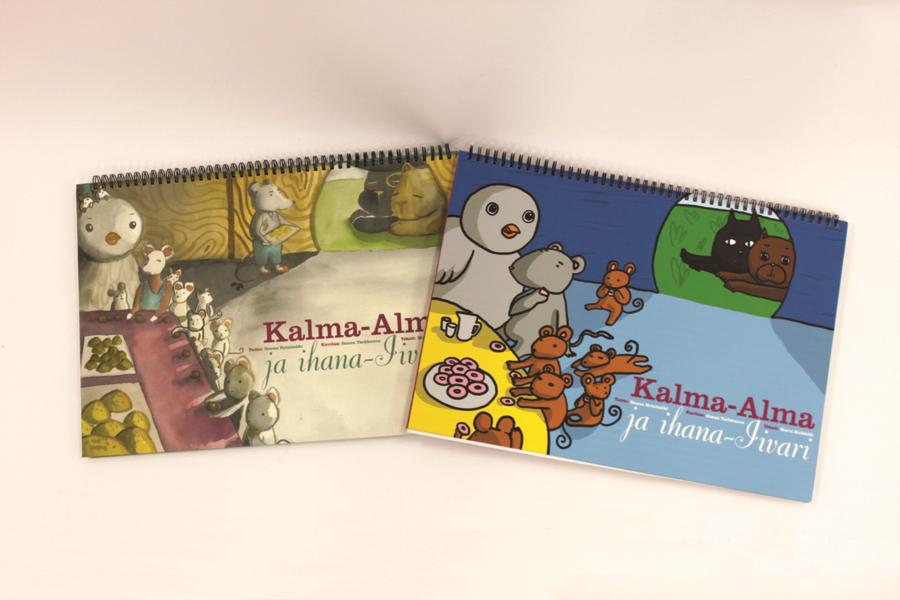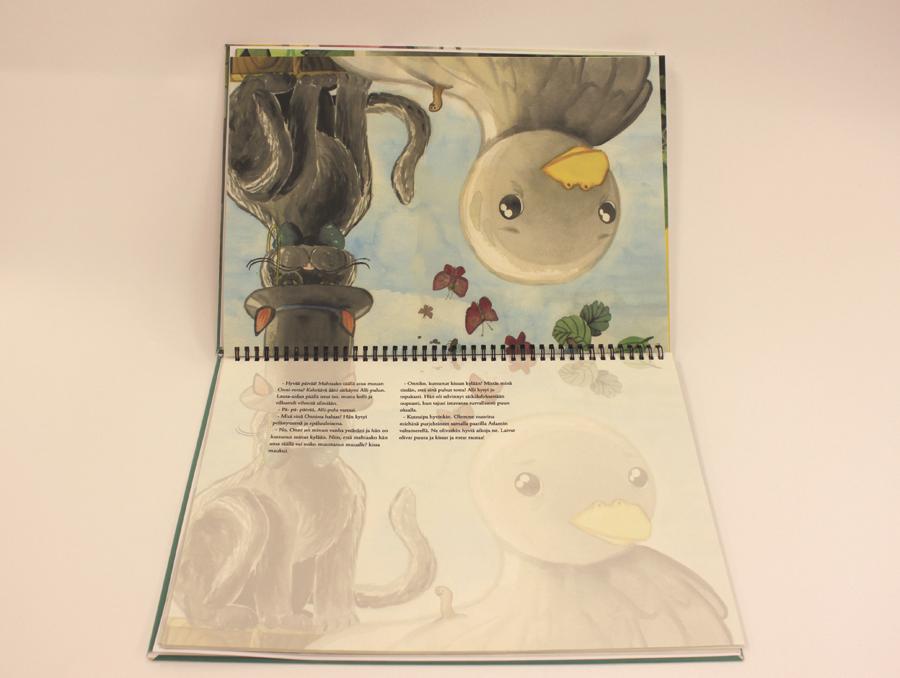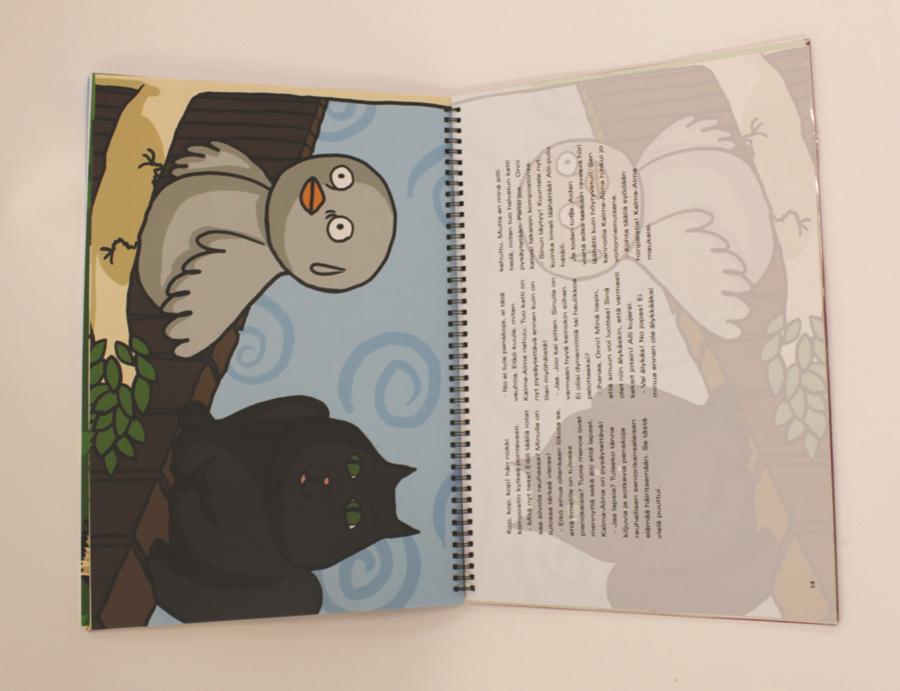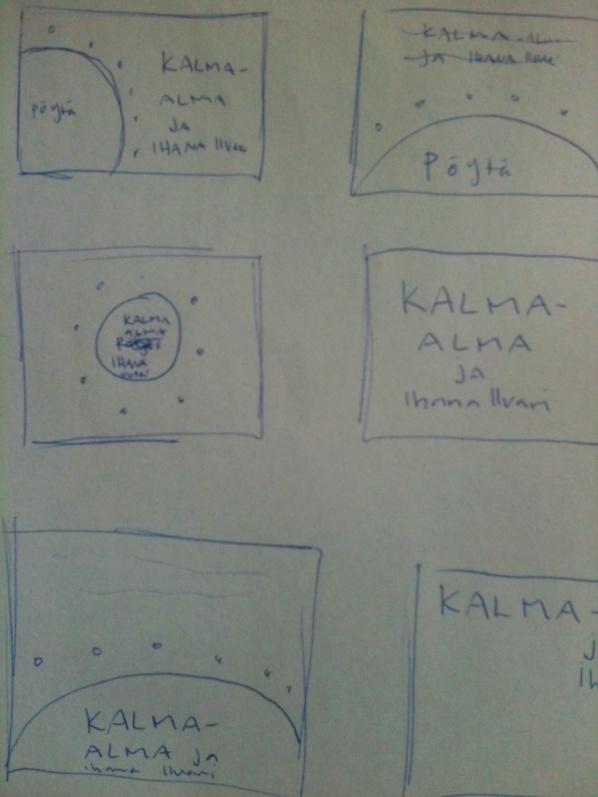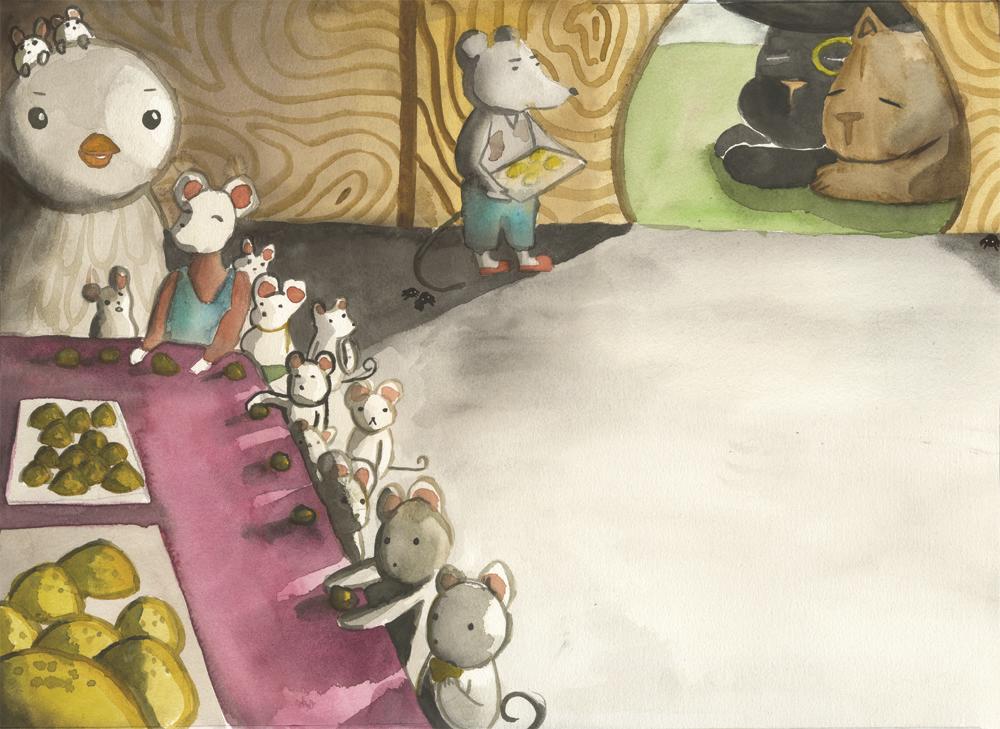
Henna Heinimäki. Taitto ja typografia lasten kuvakirjalle kirjastokäyttöön. Opinnäytetyö Kevät 2012 Kulttuurin yksikkö Muotoilun koulutusohjelma
1 Henna Heinimäki Taitto ja typografia lasten kuvakirjalle kirjastokäyttöön Opinnäytetyö Kevät 2012 Kulttuurin yksikkö Muotoilun koulutusohjelma
2 1(49) SEINÄJOEN AMMATTIKORKEAKOULU Opinnäytetyön tiivistelmä Koulutusyksikkö: Kulttuurin yksikkö Koulutusohjelma: Muotoilun koulutusohjelma Suuntautumisvaihtoehto: Graafinen muotoilu Tekijä: Henna Heinimäki Työn nimi: Taitto ja typografia lasten kuvakirjalle kirjastokäyttöön Ohjaaja: Saija Sillanpää ja Anne Kuusela Vuosi: 2012 Sivumäärä: 49 Liitteiden lukumäärä: 7 Opinnäytetyön aiheena oli suunnitella taitto ja typografia lasten kuvakirjalle. Kirja on suunnattu kirjaston satutunneille. Kirjasta oli kaksi protoa, joita testattiin. Protokirjassa oli erilaisia taitto ja typografia valintoja, joista lukija valitsi toimivimman ratkaisun. Tutkimusmenetelmänä oli haastattelu, jonka avulla kerättiin kokemusperäistä tietoa lopullisen kirjan tekemiseen. Haastattelut tapahtuivat satutunnin jälkeen haastattelemalla lukijaa. Teoriaosuudessa tarkastellaan myös mediakasvatusta satutunneilla. Avainsanat: Taitto, typografia, lastenkirja
3 2(49) SEINÄJOKI UNIVERSITY OF APPLIED SCIENCES Thesis abstract Faculty: School of culture and design Degree programme: Culture and Design Specialisation: Graphic Design Author/s: Henna Heinimäki Title of thesis: Folding and typography for children s picture book. Supervisor(s): Saija Sillanpää ja Anne Kuusela Year: 2012 Number of pages: 49 Number of appendices: 7 The goal of my thesis was to design folding and typography for children's picture book. The book was designed to be used in children's story hours in libraries. There were two prototypes of the book, which I tested. In the book there were various different folding and typography options of which the reader chose the best alternative. As a research method I used interviews which helped me to gather empirical data for making the final version of the book. The interviews took place after the story hour. In addition, in the theoretical part I reviewed media education at the story hours. Keywords: folding, typography, picture book
7 6(49) Käytetyt termit ja lyhenteet Mediakasvatus on oppimista ja kasvua media parissa. Se on toimintaa, jolla tietoisesti yritetään vaikuttaa yksilön median käyttöön ja mediataitoihin. Mediakasvatuksella kehitetään mediakulttuurissa elämisen perusvalmiuksia. Mediakasvatus on moninainen käsite ja sille ei ole yhtä ainoaa selkeää määritelmää. Mediakasvatus voi olla oppimista ja kasvua median parissa. (Mediametkaa, )
8 7(49) 1 JOHDANTO 1.1 Tavoite Tavoitteena on saada kirja julkaistua ja saada se kirjastokäyttöön. Koska kirjalle on jo olemassa käyttöliittymä tavoitteena on saada kirjaprojekti tuotua loppuun suunnittelemalla sille parhaiten toimiva taitto ja typografia, sille tarkoitetussa erilaisessa käyttöliittymässä. Lisäksi kirja tarvitsee myös kuvituksen. Tavoitteena on saada näkyvyyttä ja tietoisuutta kirjasta ja samalla tuoda omaa osaamista näkyville kirjastoissa graafisen muotoilun alalta. 1.2 Tausta Syksyllä järjestettiin lastenkirja luentoja Framilla. Luennot järjesti kirjasto- ja tietopalvelu yksikkö ja niitä ohjasi koulutusohjelmapäällikkö Sari Mäkinen-Laitila. Luennoilla käytiin mm. läpi lastenkirjojen kehitystä tähän päivään saakka sekä tutustuttiin eri kustannuslaitoksiin. Luennot olivat osa lastenkirjaprojektia, johon osallistui graafisen muotoilun 2-4- vuosikurssin opiskelijoita. Projektiin osallistui myös kirjasto- ja tietopalvelun opiskelijoita. Opiskelijat jakautuivat ryhmiin, joissa kukin ryhmä alkoi suunnitella kokeellista lastenkirjaa. Valmiit lastenkirjaprotot olivat esillä Layers- lastenkirjanäyttelyssä Vaasassa Jo edellisenä syksynä syventävän projektini aiheena oli suunnitella kokeellinen lasten kuvakirja konsepti kirjastokäyttöön. Olin havainnoimassa kolme kertaa Seinäjoen kaupunginkirjastossa lasten satutunteja ja sitä miten lapset käyttäytyivät kirjastossa. Tutkin myös lastenkirjojen käyttöä kirjastossa. Satutunneilla selvisi ongelma jota ratkaistiin. Lukijan oli vaikea lukea lapsille niin, että lapset näkisivät kuvat hyvin ja lukija näkisi tekstin samaan aikaan. Tästä syntyi idea, jonka olen nimennyt suuntakirjaksi. Kirjassa on aukeaman toisella sivulla ainoastaan kuva. Kyseessä kun on alle kouluikäiset lapset, niin heitä ei niinkään kirjaimet kiinnosta ainoastaan kuvat. Toisella sivulla on teksti ja haalistettu kuva tekstin takana ku-
9 8(49) vasivusta, jotta lukija tietää mitä toisella sivulla on. Kuvasivu on siis suunnattu vain lapsille ja tekstisivu lukijalle. Kirjan sadun on kirjoittanut lastenkirjailija Mervi Heikkilä. Oma osuuteni tässä lastenkirjaprojektissa on suunnitella taitto ja typografia kirjalle. Kuvituksen tekee Sanna Tarkkanen omana opinnäytteenään. 1.3 Yritys yhteistyökumppani Yhteistyökumppani on Avain -kustantamo. Heiltä saimme kommentteja kirjan kehittämiseen. Avain on yleiskustantamo ja on erikoistunut nimenomaan kirjastoille tehdyistä julkaisuista. Avain kuuluu BTJ-Finlandiin, joka tarjoaa keskitetysti palveluita ja kaikkea mitä voi lainata yleisille kirjastoille. BTJ on lyhenne sanasta Bibliotekstjänst. 1.4 Tutkimusmenetelmä ja tutkimusongelma Tutkimuksessa on saatava selville, minkälainen taitto ja typografia toimii tälläisessä käyttöliittymässä kirjastokäytössä? Tutkimusmenetelmänä on haastattelu, joka tapahtuu lasten satutuntien jälkeen lukijan haastatteluna Vaasassa, Laihialla, Lapualla, Jalasjärvellä ja Tampereella. Haastattelukertoja piti olla kahdeksan. Haastattelukerroista toteutui seitsemän. Tarkoitus oli mennä testaamaan kirjaa myös Peräseinäjoen kirjastoon, mutta kirjaa ei oltu lähetetty Seinäjoen kirjastosta Peräseinäjoelle sovitussa aikataulussa. Testattavassa protokirjassa on yhdeksän erilaista taittoa ja typografia kokeiluja. Joka sivulle omansa. Nämä on valittu 27 vaihtoehdosta valiten mahdollisimman erilaiset versiot, jotta lukija pystyisi valitsemaan omasta mielestään luettavimman vaihtoehdon. Kirjaa testataan ensimmäisen kerran Seamkin Layers- lastenkirjanäyttelyssä Vaasan kirjastossa. Näyttelyssä on esillä koko projektin aikana toteutuneet lastenkirjat,
10 9(49) joita on tehnyt lastenkirjaprojektissa mukana olleet. Näyttely oli Siihen mennessä piti olla valmiina proto kirjasta, jotta sitä voitiin testata ja havainnoida miten se toimii. Protoja tehdään yhteensä neljä kappaletta. Kaksi niistä on esillä näyttelyssä ja kaksi on tarkoitettu havainnointitilanteisiin testattavaksi. Kirjoissa on kaksi erilaista kuvitusta, koska parini testaa kuvituksen toimivuutta lapsilla. Haastattelun tuloksista kerätään yhtäläisyydet, joiden pohjalta rakennetaan lopullinen ja toimivin taitto ja typografia kirjalle. Lopullisesta kirjasta tehdään myös proto.
11 10(49) 2 KIRJASTOT JA MEDIAKASVATUS Kirjastojen tehtävä on ennen kaikkea kirjojen lainaaminen. Tehtäviin kuuluu myös edistää lukutaitoa, sivistystä ja kulttuuria. Kirjastoilla on myös mediakasvatuksellinen vastuu, siihen kuuluu myös satutunnit lapsille ja niiden kehittäminen. Vaikkakin sitä ei kutsuta suoranaisesti mediakasvatukseksi. Nykykirjastot ovat rikkaita mediaympäristöjä. Kirjastossa kaikenikäiset kansalaiset pääsevät käsiksi hyvin monimuotoisiin mediateksteihin: kirjoitettuun tekstiin, kuviin, liikkuviin kuviin, ääniin ja näiden erilaisiin yhdistelmiin. (Verho 2009, 9-17) 2.1 Mediakasvatus on oppimista ja kasvua media parissa. Se on toimintaa, jolla tietoisesti yritetään vaikuttaa yksilön median käyttöön ja mediataitoihin. Mediakasvatuksella kehitetään mediakulttuurissa elämisen perusvalmiuksia. (Mediametkaa, 2006, 8) Mediakasvatus on moninainen käsite ja sille ei ole yhtä ainoaa selkeää määritelmää. Mediakasvatus voi olla oppimista ja kasvua median parissa. Opinnäytetyön aihetta silmällä pitäen pääpaino on satutuntien ja lukuhetkien kasvatuksellinen osuus lapsille. Mediatarinat tempaavat lapsen mielikuvitusmaailmaan ja antavat ideoita leikkeihin. Samaistumiskokemukset tarinoiden hahmoihin voi olla hyvinkin voimakkaita niin, että lapsi tuntee olevansa jokin hahmo päiväkausia. Median aikaansaamia tunteita jäsentää kehittyvä kyky ymmärtää faktaa ja fiktiota. Kehittyvä syy-seuraus-suhteiden taju lisää oppimista ja auttaa juonikokonaisuuksien ymmärtämisessä. Media antaa myös malleja tunteiden ilmaisuun, tunteiden nimeämiseen ja käsittelyyn. Lapsi löytää usein lempisatunsa, jota hän jaksaisi kuunnella loputtomiin. (Mediametkaa 2006, 18) Mediakasvatuksessa ei korosteta tietokoneita tai teknologiaa. Se voi parhaimmillaan olla yhdistävänä tekijänä lapsen ja aikuisen välisessä vuorovaikutuksessa. On tärkeää muistaa ottaa lapsi huomioon. Mediakasvatusta on jokaisessa ympäristössä, jossa lapsi toimii tai on tekemisissä median kanssa. Näihin ympäristöihin kuuluu tärkeänä osana kirjastot.
12 11(49) Päämääränä on kehittää ilmaisu- ja vuorovaikutustaitoja, edistää median aseman ja merkityksen ymmärtämistä sekä kehittää median käyttötaitoja. Viestintätaidosta painotetaan osallistuvaa, vuorovaikutuksellista ja yhteisöllistä viestintää. Mediataitoja tulee harjoitella sekä viestien vastaanottajana että tuottajana (Verho 2009, 11) Kirjastoissa on mediakasvatuksen tilanne hieman erikoinen. Kirjastoja ei velvoiteta mediakasvatukseen, koska kohtaa mediakasvatus ei löydy kirjastolaista. Kirjastoissa on kuitenkin järjestetty kauan satutunteja, kirjastonkäytön opetusta, innostettu lukemaan ja kirjavinkaus. Nämä asiat kertovat siis aivan muuta. Suurimmiksi esteiksi on todettu kirjastojen vähäiset resurssit ja tietämättömyys mediakasvatuksesta. Monissa kirjastoissa on otettu mediakasvatus tärkeäksi osaksi kirjaston toiminta ja se työllistää ihmisiä, mutta näin ei kuitenkaan kaikissa kirjastoissa. Kirjastoissa tarvitaan toimintakulttuurin muutosta sekä mediakasvatus selkeästi määritellyksi yhdeksi kirjastotyön osa-alueeksi. Tulevaisuuden kirjastotyöntekijä ei välttämättä ole pelkästään kirjastoalan koulutuksen saanut vaan voi edustaa myös jotain toista ammattikuntaa. (Verho 2009, 12) 2.2 Satutunnit kirjastossa Kirja on suunnattu kirjaston satutunneille lapsiryhmille luettaessa. Kirjaston satutunneilla käy alle kouluikäisiä lapsia. Satutunnit järjestetään aamupäivisin, joten koululaiset eivät pääse silloin paikalle. Alle kouluikäisillä tarkoitetaan 3-6 vuotiaita lapsia. Satutunti kestää yleensä minuuttia, koska lapset eivät jaksa kauempaa kuunnella ja olla paikoillaan. Satutunnilla kirjastohoitaja tai joku ulkopuolinen henkilö lukee lapsille satuja. Lapset istuvat lukijan ympärillä ja seuraavat kuvia ja kuuntelevat tekstiä. Lukijan on tärkeää muistaa katsekontakti lapsiin, niin lapsille tulee olo, että heille luetaan. Tärkeää on myös vuorovaikutus. Lapset jaksavat paljon kauemmin olla rauhassa ja kuunnella, kun lukija tekee välillä kysymyksiä lapsille vaikkapa kirjan kuvista. Lapset vastaavat aina innoissaan. Vuorovaikutuksen
13 12(49) keinoja ovat katsekontaktit, ilmeet, eleet, liikkeet ja kieli. Suurin osa vuorovaikutuksesta on tiedostamatonta. (Mediametkaa 2006, 34) Satutunteja on järjestetty kirjastoissa jo melkein sata vuotta. Aluksi satutunnit olivat ruotsinkielisiä ja niitä järjestettiin vain Helsingissä. Satutuntitoiminta alkoi vähitellen levitä muualle Suomeen. Satutuntien suosio oli siihen aikaan suuri, koska muita tapahtumia ja ohjelmia ei ollut tarjolla. Kirjastot olivat lähes ainoa paikka pyhäkoulun lisäksi, johon lapsia voitiin viedä saamaan iloa, virkistystä ja opetustakin. (Mäkelä 2002, 13) Mäkelä sanoo kirjassaan Satuseikkailu kirjastossa, että kirjasto on lasten paikka. Jätetään entisaikaisten, yksisuuntaisten satutuntien pito. Järjestetään niiden sijaan satutuokioita, vuorovaikutteisia hetkiä, jossa lapset saavat olla mukana satua kertomassa, tekemässä ja elämässä. Satutunnilla käymisessä on lapsille hyötyä. He oppivat käymään kirjastossa. Suurin osa lapsista, jotka tulevat satutunnille ovat innoissaan. Heistä näkee, että he viihtyvät kirjastossa ja sinne on kiva tulla.
14 13(49) 3 KIRJAGRAFIIKKA 3.1 Kirjan suunnittelu ja taitto Julkaisua tai sen sivua ei ole olemassa ilman visuaalista rakennetta. Visuaalinen rakenne koostuu kirjan ulkoasusta, miltä kirja näyttää katsojan silmään. (Kuvakulmia 2, 2010, 59-60) Suunnittelija tekee kirjalle muodon ja ulkonäön. Taitto on suunnittelijan käsialaa, jossa suunnitellaan tarkoituksen mukainen typografia, palstojen muoto, taiton tyhjä tila, kuvat, värit ja paperilaatu. Kuvan ja tekstin oikeanlaisella yhdistämisellä on suuri visuaalinen voima taitossa. Yhä useammin kuitenkin tuotetaan kirjoja, joissa ei käytetä apuna kuvan ja tekstin yhdistämistä, vaan kuvan tueksi tuodaan kuvateksti tai kaavio selventämään viestiä. (Wilson 1993, 67) Kuvan ja tekstin funktio Graafisella suunnittelijan haasteet taittamisessa on yhdistää kuva ja teksti ja luoda ei-verbaalisia viestejä lukijalle. Kuinka tehdä niistä yhtenäinen kokonaisuus? Perinteisesti teksti on dominoivaa ja kuvat vain seuraavat sitä. Kuva ja teksti täydentää toisiaan. Kuvan yksityiskohdat selkeytyvät tekstin avulla. Kuvilla voidaan selvittää kenestä on tekstissä kyse tai vaikka tapahtumien paikan. Teksti voi olla tehokas keino selvittää kuvan merkitystä ja tulkitsemaan sitä. Kuvan ja tekstin rinnakkain asettaminen tavanomaisesti, niin että kuva on aukeaman toisella sivulla ja teksti toisella sivulla. Kuvan ja tekstin jakaminen eri osiin, niin että kuva on esimerkiksi aukeaman toisella sivulla ja teksti toisella, se sallii sen, että kuvaa ja tekstiä pystyy tulkitsemaan ilman rajapintoja. Suunnittelijat pyrkivät yhdistämään tai asettamaan rinnakkain kuvan ja tekstin uudella odottamattomalla tavalla, joka lisää viestin voimaa. (Meggs 1989,41-45)
15 14(49) Kirjan kansi Yleensä kirjatkin valitaan kannen visuaalisuuden perusteella. Kansi ohjaa ostajaa tai käyttäjää valitsemaan mieluisan kirjan hankittavaksi. (Meggs 1989,41-43) Kirjan kannessa on yleensä kirjan nimi ja tekijät. Se on kirjan otsikko. Otsikon tehtävä on houkutella lukijaa lukemaan kirja, sen tulee olla visuaalisesti mielenkiintoinen. Otsikon tehtävä on myös antaa lukijalle kuva kirjan yleisestä sävystä ja yhtenäisyydestä. Otsikko on sivun vahvin yksittäinen typografinen elementti, jonka koko, muoto ja sijoittelu vaikuttaa määräävästi koko julkaisun ilmeeseen Otsikon pitää kantaa visuaalisesti koko muun kirjan typografian yli. Liian pienet otsikot näyttävät merkityksettömiltä, liian suuret taas hallitsevat liikaa koko kantta tai aukeamaa. (Lyytikäinen & Riikonen 1995, 35) 3.2 Typografia Luettavuus on yleensä kirjan perusvaatimus ja oletus. Hyvä luettavuus on hyvien kirjaintyyppien ja sopivan sommittelun yhdistelmä. Kirjan typografia määritellään taittovaiheessa. Taitossa valitaan tilanteeseen sopivimmat ja luettavimmat kirjaintyypit. Typografisilla valinnoilla voidaan vaikuttaa siihen, minkälainen tunne julkaisusta välittyy lukijalle. Typografiaan vaikuttaa myös se, että missä kirjaa tullaan käyttämään. Täydellinen typografia vaatii täydellistä kaikkien sen elementtien harmoniaa. Harmonia tarkoittaa sopusuhtaisia mittasuhteita. Niitä on joka paikassa: marginaalien koossa ja niiden keskinäisissä suhteissa kirjan sivuilla, rivivälin suhteissa verrattuna marginaalien mittoihin, sivunumeron sijoittamisessa, versaalikirjainten välistyksessä. Kaikki elementit ovat sidottuina toisiinsa. (Brusila 2001, 54) Brusilan mielestä huonoon typografiaan totutaan. Monet lukevat enemmän sanomalehtiä kuin kirjoja, ja ovat siksi yleensä tekemisissä huonon typografian kanssa. Huonoon ruokaan totutaan, kun parempaakaan ei ole saatavilla, samalla tavoin totutaan huonosti suunniteltuun typografiaan. Hyvä typografia ei ole lystikästä, se on tarkan ja tahdikkaan suunnittelun lopputulos. Typografia on hyvä vain silloin,
16 15(49) kun jokainen sen osanen on liitoksissa sen toiseen osaseen. Kirjan ikään vaikuttaa sen typografia, mitä tasapainotetumpi ja sopivampi sen typografia on sitä kauemmin kirja elää. Kirjainten luettavuus perustuu nopeaan tunnistettavuuteen ja tiettyjen kirjaintyyppien opittuun lukemiseen. Leipäteksti tulee siis aina latoa sellaisella kirjaintyypillä, jonka hahmon tunnistettavuus on hyvä. Ladotusta tekstistä tekee helposti luettavan x-korkeus, kirjainkoko, rivin pituus (palstan leveys), riviväli ja palstaväli. Ne on aina määriteltävä suhteessa toisiinsa. (Lyytikäinen & Riikonen 1995, 40) Kirjaintyypit ja luettavuus Leipäteksti on julkaisun perusteksti, jolla kaikki varsinainen teksti ladotaan. Leipäteksti ladotaan pienellä pistekoolla ja sen tulee olla mahdollisimman hyvin ja helposti luettavaa. Hankalalukuinen leipäteksti ei houkuttele lukemaan. Leipätekstin on hyvä latoa sellaisella kirjaintyypillä, joka on helposti tunnistettava. Erikoiset ja oudot kirjaintyyppi valinnat kuuluvat ennemmin otsikoihin. Kannattaa siis valita sellainen tekstityyppi, jonka pylväiden ja hiusviivojen välinen kontrasti ei ole kovin suuri. (Lyytikäinen & Riikonen 1995, 38) Vanha uskomus on, että antiikvakirjain on aina helppolukuisempaa kuin groteski. Näidenkin kirjainten luettavuus liittyy kuitenkin oppimiseen. USA:ssa tehdyn tutkimuksen mukaan antiikva on luettavampaa, koska siihen on totuttu. Euroopassa on sen sijaan käytetty enemmän groteskia, joten groteskiteksti on saanut parempia luettavuustuloksia, kuin USA:ssa. Antiikvakirjaimen etuna leveillä palstoilla on se, että antiikvan päätteet vievät silmää eteenpäin luettaessa. Kapeilla palstoilla kuitenkin on päätteettömien kirjainten luettavuus yhtä hyvä, kuin päätteellisten. Groteskitekstin luettavuus heikkenee, kun palstan leveys kasvaa. Esimerkiksi kirjoissa on usein antiikvateksti varmempi valinta. Antiikvan ja groteskin valintaan vaikuttaa tietenkin myös se, että minkälainen teksti on kyseessä. (Lyytikäinen & Riikonen 1995, 39)
17 16(49) Kuvio 1. Vasemmalla groteskitekstiä ja oikealla antiikvatekstiä. (Lyytikäinen & Riikonen 1995, 47) Etsittäessä mahdollisimman luettavaa kirjaintyyppiä on otettava huomioon suuret avoimet silmukat: kavennetun kirjaintyypin n ei saa näyttää r:ltä tai h:lta. Riittävä x- korkeus: vaikuttaa kirjaimen näennäiseen kokoon enemmän kuin varsinainen pistekoko. Sopivat päätteet: liian koristeelliset tai ohuet päätteet eivät ole hyvästä luettavuuden kannalta. Kohtuullinen kontrasti: kirjainosien kontrasti ei saa olla liian suuri. Sopiva leikkaus: sekä liian laihat että liian lihavat kirjainmuodot heikentävät luettavuutta. Esimerkin pistekoko on sama, mutta x-korkeudessa on suuria eroja (Lyytikäinen & Riikonen 1995, 39-40) Kuvio 2. Esimerkki x-korkeudesta. (Itkonen 2007, 84)
18 17(49) Kirjainväli ja merkkiväli Ladelmaa tehdessä täytyy ottaa huomioon myös kirjainvälit ja merkkivälit. Itsestään selvästi liian tiheä tai harva kirjainväli tekee lukemisen vaikeammaksi. Kirjainväli vaikuttaa myös ladelman yleiseen ilmeeseen. Kirjainten tulisi näyttää yhtä kaukana olevilta. Liian suuret sanavälit tekevät lukemisesta töksähtelevää. Esimerkin alimmaisessa rivissä on liian suuri kirjainväli suhteessa sanaväleihin. (Lyytikäinen, Riikonen 1995, 41) Kuvio 3. Esimerkki sana- ja kirjainväleistä. (K. Lyytikäinen, H. Riikonen 1995, 41) Palstat ja riviväli Kun tehdään taittoa jossa on paljon tekstiä, niin tehdään myös palstoja. Palstojen suunnittelussa on olennaista ottaa huomioon leipätekstin kirjainkoko, palstan muoto, rivivälin suuruus ja palstaväli jos palstoja on enemmän kuin yksi. Suomessa on tapana latoa tasaan kun taas esimerkiksi muualla Euroopassa ja USA:ssa on yleisempää latoa leipäteksti liehureunaiseksi. (Lyytikäinen & Riikonen 1995, 43) Rivivälin avulla säädellään tai palstan näkövaikutelmaa sitä miltä kuinka tiiviiltä tai väljältä teksti näyttää. Hiukan väljennetty riviväli houkuttelee paremmin lukijaa kuin tiivis. Yleensä leipätekstin riviväli on 1-4 pistettä suurempi kuin kirjainkoko. Palstaväli on yhtä suuri tai mieluiten hiukan suurempi, kuin tekstissä käytetty rivi-
19 18(49) väli. Merkkien määrä rivillä on myös tärkeää ottaa huomioon. Jos merkkejä on liikaa luettavuus kärsii. Yleisesti ottaen hyvä merkkien määrä riville on merkkiä. (Itkonen 2007, 83-95) Rivivälin määrittelemiseen on olemassa nyrkkisääntöjä, jotka eivät kuitenkaan takaa aina varmaa tulosta. Hyvä luettavuus on suhteiden summa. Kirjainkoossa 6-9 pt rivivälin tulee olla vähintään yhtä pistettä suurempi kuin kirjaimen pistekoko. Kirjainkoossa pt rivivälin pitää puolestaan olla kahta pistettä suurempi. Mitä suurempi pistekoko, sen suurempi suhteellinen riviväli. (Lyytikäinen & Riikonen 1995, 41) Alla olevassa kuviossa on ylemmässä palstassa on liian pieni riviväli Times 10/10. Alemmassa esimerkissä huomaa kuinka rivivälin suurentaminen parantaa luettavuutta Times 10/12. (Lyytikäinen & Riikonen 1995, 44) Kuvio 4 Riviväli esimerkki. Kuvio 5. Minion 9/10. Esimerkki rivistä, jossa on liikaa merkkejä.
20 19(49) Kuvio 6. Minion 9/10. Sama pistekoko ja riviväli kuin edellisessä kuviossa. Hyvin ladottu leipäteksti muodostaa tasaisen harmaan pinnan. Kauniissa palstassa ei pidä olla suurien sanavälien muodostamia purosia eikä leipätekstin eri kirjainten kontrasti saa olla häiritsevän suuri. Rivivälitkään eivät saa muodostaa suhteettoman paksuja valkoisia palkkeja tekstiin. (Lyytikäinen & Riikonen 1995, 41)
21 20(49) 4 KALMA-ALMA JA IHANA-IIVARI KIRJAN TAITTO JA TYPOGRAFIA Kirjasta on kaksi erilaista protoa, joita testataan. Kummassakin on erilainen kuvitus. Muuten kirjat eivät eroa toisistaan. Protokirjat on valmistettu graafisen muotoilun osaston laitteilla. Niistä on tehty mahdollisimman oikean näköisiä. Kuvio 7. Kirjat yhdessä Kirjassa on yhteensä 9 kuvasivua ja 9 tekstisivua. Joka toisella sivulla on tekstiä ja joka toisella pelkkä kuva. Jokaisella tekstisivulla on erilainen taitto ja typografia. Tämä sen takia, että pystyttäisiin testaamaan mahdollisimman monta erilaista taittoa ja typografiaa käytännössä.
22 21(49) Kuvio 8. Kirjat Layers-lastenkirjanäyttelyssä Vaasassa. Kuvio 9. 1 protokirjan aukeama
23 22(49) Kuvio protokirjan aukeama 4.1 Kirjan typografia valikoitui taulukon avulla, jossa on 27 erilaista typografiavalintaa. Näistä 27 valikoitui 9, jotka ovat protokirjassa. Valitut typografiat ovat mahdollisimman erilaisia toisiinsa verrattuna, että lukija huomaa eron selvästi ja osaa valita omasta mielestään parhaimman. Alla olevassa taulukossa oranssilla pohjalla on valitut typografiat. Alla on myös valikoidut koeladelmat. Liitteessä on kaikki koeladelmat järjestyksessä. Kaikkia liitteissä ja kuvioissa esiintyviä koeladelmia on pienennetty 30% alkuperäisestä. (Liite 1)
24 23(49) Taulukko 1. Koeladelmat. Kirjan kolme ensimmäistä typografia valintaa ovat groteskeja. Kirjaintyyppinä niissä on Univers. Universin suuri etu on sen suuri, yhtenäinen kirjainperhe. Universvalikoimalla voi tehdä minkä tahansa työn, johon groteski ylipäätään sopii. Koska Universin muotoilu on hiukan eloisampaa ja paksuusvaihtelua on enemmän kuin esimerkiksi Helveticassa, sen lukeminen ei ole yksitoikkoista. (Itkonen 2007, 53)
25 24(49)
26 25(49) Kuviot Groteskit koeladelmat. Kolme seuraavaa typografiavalintaa ovat antiikvoita eri antiikvaluokista. Renesanssiantiikvana on Adobe Garamond. Renessanssiantiikvojen luettavuus on hyvä, sillä se kehitettiin nimenomaan pitkien tekstien kirjojen lukemista varten. Niiden viivakontrasti on riittävä antamaan tekstille eloisuutta, mutta ei niin vahva, että se alkaisi häiritä ja väsyttää lukijaa. (Itkonen 2007, 32) Toinen antiikva on siirtymäkauden antiikva. Kirjaintyyppinä on Baskerville. Siirtymäkauden antiikvoista Baskerville on suosituin. Sen luettavuutta pidetään yleisesti hyvänä; kuitenkin lisääntynyt kontrasti saattaa jopa vaivata lukijoita. Kolmas antiikva on siirtymäkauden antiikva. Kirjaintyyppinä on Bodoni. Bodonin hiusviivat ovat erittäin ohuita ja kontrasti suuri. Mikä tekee siitä leipätekstikoossa vaikeasti luettavan ja vaikeasti painettavan. Ohuiden viivojensa takia Bodoni ei ole edukseen 10:tä pistettä pienempänä. (Itkonen 2007, 37)
27 26(49)
28 27(49) Kuviot Antiikva koeladelmat. Kirjan viimeiset kolme typografiavalintaa ovat egyptiennejä, jossa kirjaintyyppinä Clarendon light. Itkosen mielestä egyptiennet ja clarendonit jakautuvat eri luokkiin: Egyptiennestä kehittyi clarendon, joka pienellä alkukirjaimella kirjoitettuna tarkoittaa kirjaintyyliä mutta suurella alkukirjaimella kirjaintyyppiä. Clarendon on suunniteltu otsikko- ja mainoskäyttöön. Monirivisiin teksteihin se on liian vahvapiirteistä ja lihavaa. Myöhempi light-versio on kyllä tarpeeksi laihaa leipätekstiin mutta muotoilultaan yhtä rasittavaa kuin Regular. (Itkonen 2007, 47) Kuitenkin Lyytikäinen kirjassaan Painotuotteen suunnittelu, laittaisi clarendon kirjaintyypin kuulumaan egyptienneihin. (Lyytikäinen & Riikonen 1995, 28)
29 28(49)
30 29(49) Kuviot Egyptienne koeladelmat. 4.2 Kirjan kannen typografia Kirjan kannen typografiaa lähdettiin suunnittelemaan lapsille. Kannen typografiassa täytyisi herättää lapsen mielenkiinto kirjaa kohtaan, vaikka lapsi ei osaisi lukea ja sen täytyy sopia kuvitukseen sulavasti, niin että se on osa kuvaa. Kirjan nimi Kalma-Alma ja Ihana-Iivari viittaa jo siihen, että toinen kirjan hahmoista on pelottava ja toinen on kiltti. Tätä seikkaa pyrittiin tuomaan kannen otsikko typografiassa esille. Typografialla lisättiin Kalma-Alman pelottavuutta ja Ihana-Iivarin ihanuutta. Seuraavassa kolme esimerkki luonnosta typografiasta. Loput kannen typografia kokeilut liitteenä (Liite 2)
31 30(49) Alma Kuvio 20. Esimerkkejä kannen typografia kokeiluista. Kun luonnoksia oli suunniteltu ilman kuvaa alettiin suunnittelemaan kannelle kuvaa yhdessä kuvittajan kanssa. Sadun lopussa kaikki hahmot kerääntyvät pöydän ympärille syömään pullaa, tätä ideaa pidettiin hyvänä vaihtoehtona kannen kuvaksi. Typografiaa alettiin luonnostelemaan kanteen ennen kuin lopullinen kuva oli selvil- ihana-
32 31(49) lä. Ainoastaan tiedettiin että kanteen tulee pöytä ja hahmoja sen ympärille, joten tätä käytettiin pohjana kannen typografian asettelulle. Kuvio 21. Kannen luonnostelua. Kuvio 22. Kannen kuvitus valmiina ilman typografiaa.
33 32(49) Kuvio 23. Protokirja 1 valmis kansi. Kannen typografiaksi valikoitui Clarendon Lstd regular ja UniversityRomanStd regular. 4.3 Kirjan taitto Kirjan koko on kannessa 395x280 ja sivuissa 390x275. Kirjassa on kannet ja 22 sivua. Kirjan vierukset on vasemmalla Kirjassa on kierteet, jotta sivut pystyttäisiin kääntämään kokonaan ympäri, joka on selaustavan kannalta olennaista. Kirja on taitettu Adobe InDesign ohjelmalla. Kirjan vierus vasemmalla on 60 mm, oikealla 130 mm ja ylhäällä 30 mm. Palstojen alareuna tasataan aina tasan toiseen palstaan nähden. Muuten rajoituksia ei ole. Kirjan lopulliseen versioon valittiin tasapalsta, koska se lisää luettavuutta tässä tarkoituksessa. Tasapalstan etuna on se että se on sommittelullisesti helppo ja antaa sivulle ryhtiä. (Liitteet 3-4)
34 33(49) 4.4 Satu Satu on lastenkirjailija Mervi Heikkilän kirjoittama. Satu kertoo eläimistä. Sadussa on ilkeä kissa Kalma-Alma, joka kiusaa hiiriä. Lopuksi kuitenkin hiiret ja kissat ovat sulassa sovussa, koska kuvaan astuu Ihana-Iivari, joka lepyttää Kalma-Alman. (Liite 5) Satu on tarkoitettu n. 4-6 vuotiaille, koska tekstissä on muutamia vaikeita sanoja, joita pienemmät lapset eivät ymmärrä.
35 34(49) 5 TUTKIMUS JA TIEDONHANKINTA Teoriaosuuden lisäksi tiedonhankintamenetelmänä on haastattelu, joka on dokumentoitu kirjallisin muistiinpanoin. Haastattelulla kerätään empiiristä, eli kokemusperäistä tietoa kirjallisen aineiston lisäksi. (Liite 4. kysymykset) (Hirsjärvi & Hurme, 2001) Haastattelu on valittu tähän tiedonhankinta menetelmäksi, siksi koska on saatava suoraan tietoa itse käyttäjältä, kirjan käyttämisen jälkeen. Haastattelut suoritettiin satutunnin jälkeen haastattelemalla kirjan lukijaa. Kysymyksiä, joita kysyttiin lukijalta oli yhteensä kuusi. 5.1 Lukijat ja lapset satutunneilla Satutunneilla käytiin testaamassa kirjaa yhteensä seitsemän kertaa. Alun perin tutkimussuunnitelmassa kertoja on kahdeksan. Yksi kerta jouduttiin perumaan. Satutunneilla oli vaihtelevasti lapsia. Välillä lapsia saattoi olla vaan kolme ja välillä lähes neljäkymmentä. Lapsien lukumäärä ei kuitenkaan vaikuttanut tutkimukseen. Lukijoita oli erilaisia. Kolme oli kirjastonhoitajia, kaksi lukijaa oli opiskelijoita ja kaksi oli ulkopuolisia lukijoita, jotka lukivat vapaaehtoisesti satutunneilla. Toisilla oli pitkä kokemus satutunneilla lukemisesta ja toisilla taas ei. Lukijan kokemuksella ja varmuudella oli suuri merkitys satutunnin kulkuun. Ne lukijat, joilla oli usean vuoden kokemus satutuntien pitämisestä, olivat paljon eläytyväisempiä lukijoita ja he kyselivät lapsilta satuun liittyviä kysymyksiä kesken sadun. Tämä piti lasten mielenkiinnon yllä. Ne lukijat, joilla oli vähemmän kokemusta lukivat sadun niin, että he eivät ottaneet lapsia huomioon sadun aikana. Lapset eivät jaksaneet keskittyä yhtä hyvin. Varsinkin kun satu oli pitkä, oli tärkeää että lasten mielenkiinto pidettiin yllä kysymyksillä. Lukijaa haastateltiin satutunnin jälkeen, kun hän oli lukenut kirjan. Lukijalta kysyttiin kuusi kysymystä kirjan toimivuuteen liittyen. Kysymysten vastausten perusteella kootaan lopullinen kirja. Kysymykset liitteenä (Liite 6)
36 35(49) Vaasan kaupunginkirjasto Satutunti pidettiin Layers-lastenkirjanäyttelyn yhteydessä. Lukijana Kirjasto- ja tietopalvelun opiskelija. Kokemusta muutamista satutunneista. Lukijan mielestä teksti saa olla isoa. Kaksi ja kolme palstainen toimi hyvin. Toinen sivu oli mieluisin lukea. Lukija ymmärsi heti kuinka kirjaa käytetään. Kirjaa oli kiva pitää sylissä, joka helpottaa lukuhetkeä. Oli hyvä että kuva oli tekstin takana, niin tiesi mitä kuvasivulla tapahtuu. Kierre toimii tarkoituksessaan hyvin. Kirja ei ollut liian pieni lukijan mielestä. Se saa olla suuri, niin kuvista saa selvää. Idea toimii satutunti käytössä hyvin. Lapset jaksoivat kuunnella koska he näkevät kuvat koko ajan, lukija sanoo Laihian kunnankirjasto Lukijana oli kirjastonhoitaja, jolla oli satutunti kokemusta noin viisi vuotta. Lukijan mielestä teksti oli liian ylhäällä. Jos teksti olisi alempana, kirjaa pystyisi pitämään helpommin ja samalla saisi paremmin katsekontaktin lapsiin. Ensimmäisen sivun teksti oli paras. Toisella sivulla teksti oli liian isoa ja kohta jota luettiin katosi helposti. Kierre ei toiminut niin hyvin kuin olisi ajatellut. Kirjan käyttötavan oli helppo ymmärtää. Kuva tekstin takana ei häirinnyt. Jos kirja olisi pystysuuntainen, niin sivujen kääntely voisi olla helpompaa, koska normaaliakin kirjaa luetaan niin. Kirja oli melko suuri ja se painoi liikaa. Sitä oli sen takia vaikea pitää ylhäällä. Kuvat näkyivät kyllä kauas, joka oli hyvä koska lapsia oli 37! Tarkoituksessaan kirja toimii hyvin Vaasan kaupunginkirjasto Lukijana kirjastonhoitaja, jolla kokemusta satutunneista n. kahdeksan vuotta. Kaksi ja kolme palstaiset sivut olivat parhaita. Liian pientä tekstiä nelos-sivulla. Mitä suurempi teksti sen helpompi lukea tässä tarkoituksessa, koska kirjaa piti pitää melko kaukana. Sivua neljä oli myös kiva lukea, mutta paras sivu oli ensim-
37 36(49) mäinen. Kirja ei lukijan mielestä tarvitse käyttöohjeita, koska käytön kyllä ymmärtää, kun kirjaan saa tutustua. Kuva tekstin takana ei häirinnyt. Kirjan kierre toimii tarkoituksessaan hyvin. Sivujen vaan täytyy olla vahvoja, että ne ei kulu käytössä. Monesti näkee kirjoja, joissa kierre on repinyt ohuet sivut reunasta. Kirja on sopivan kokoinen, ei ainakaan liian pieni. Sitä on hyvä pitää sylissä. Hyvät tukevat kannet auttaa kirjan pitelyä. Tässä tarkoituksessa kirjan selaustapa toimii erinomaisesti, mutta ei niinkään kotikäytössä. Lukija oli joskus valmistellut satutunnin niin, että hän oli kirjoittanut tietokoneella sadun kirjan taakse, että hän pystyisi pitämään kirjaa koko ajan lapsiin päin. Kalma-Alma ja Ihana-Iivari satu oli lian pitkä satutunnille lukijan mielestä Tampereen pääkirjasto Metso Lukijana oli kasvatustieteiden opiskelija, joka oli aiemmin pitänyt muutamia satutunteja. Lukijan mielestä iso teksti toimii hyvin. Ensimmäinen sivu oli paras. Lukija ei heti ymmärtänyt kuinka kirjaa käytetään. Kirja oli kädessä väärinpäin. Kirjaan pitää tottua ja sitä pitää hieman opetella käyttämään hänen mielestään. Suuri plussa oli kuva tekstin takana. Auttoi hahmottamaan hyvin tapahtumia. Sivujen kääntely oli helppoa, kun siihen tottui. Kirja on parempi mitä suurempi se on. Tämän kokoinen kirja on juuri sopiva, sitä jaksoi pitää hyvin sylissä. Kirjan erilainen selaustapa toimi. Kirjan kierteen täytyy olla suuri, jotta sivut kääntyvät helposti. Lukija olisi mielellään lukenut kirjan myös seuraavalla satutunnilla Laihian kunnankirjasto Lukijana kirjastonhoitaja, jolla kokemusta satutunneista yli 20 vuotta.
38 37(49) Lukijan mielestä sivulla kaksi oli liian suuri kirjainkoko. Päätteellinen fontti paras, koska siinä on hyvä rytmi. Sivu neljä oli paras. Lukija ymmärsi heti kuinka kirjaa käytetään. Oli nähnyt lehdessä jutun kirjasta. Hän mainitsee kuitenkin, että olisi hyvä mainita jossain kohtaa, että kuva tekstin takana on peilikuvana, mutta muuten kuva tekstin takana on erinomainen. Kierre saisi olla suuri, jotta sivut kääntyisivät helposti. Kirjan koko oli hyvä lukijan mielestä. Helppo pitää myös korkealla, eikä se painanut liikaa. Kirjan erilainen selaustapa toimi hänen mielestä paremmin kuin olisi ajatellut. Hän olisi halunnut kysellä kuvista lapsilta enemmän, koska siihen oli erinomainen mahdollisuus tässä kirjassa Jalasjärven kunnankirjasto Lukijana graafisen muotoilun opiskelija, jolla ei aiempaa satutunti kokemusta. Lukijan mielestä antiikva kirjaintyyppi oli ääneen luettaessa huonompi, kun taas groteski toimi paremmin. Ensimmäinen sivu oli mieluisin lukea. Toisella sivulla teksti oli liian suurta. Kirjan käyttötapa oli heti selvää, kun aukaisee ensimmäisen aukeaman niin sen ymmärtää heti lukija sanoo. Lukija piti siitä, että kuva oli tekstin takana, koska siitä näki mitä tapahtui toisella puolella. Antiikvan kohdalla se ei toiminut, koska kuva ja teksti sekoittuivat. Sivujen kääntely oli helppoa kierteen ansiosta. Kirja oli lukijan mielestä hieman liian suuri lukijalle, mutta kun ajattelee satutunteja ja kuvan pitää näkyä kauas niin siinä tarkoituksessa koko on hyvä. Hän ei muuttaisi kokoa, koska tärkeintä on että lapset näkevät kuvat. Selaustapa toimi hyvin, koska lapsiin sai hyvin katsekontaktin ja koska toisella sivulla on ainoastaan kuva, niin teksti ei ole häiritsemässä lapsia Lapuan kaupunginkirjasto 9.4. Lukijana ulkopuolinen lukija, joka on pitää satutunteja vapaaehtoisesti satunnaisesti. Ensimmäinen sivu miellytti lukijaa eniten. Toinen sivu toimi myös hyvin. Teksti saa olla suurta, jotta sitä on helppo lukea kauempaa. Lukija ei ymmärtänyt heti kuinka
39 38(49) kirjaa käytetään. Ensin hän ajatteli, että mikä tämä tällainen sylikirja oikein on, että miten lapset tästä näkevät kuvat! Mutta kirjan tarkoitus aukeni kuitenkin melko nopeasti. Kuva tekstin takana ei häirinnyt. Kierre toimi erinomaisesti, vaikka tämän kirjan sivut olivat liian paksuja ja tekivät kääntelystä hieman vaikeaa. Kirjaa sai hyvin pidettyä polvilla. Kirjan koko oli hieman liian suuri. Erilainen selaustapa toimi satutunti käytössä hyvin. 5.2 Yhteistyökumppanin mielipiteet ja kommentit Kierrekansista: uskon, että ne toimisivat hyvin ja lisäisivät kirjan ansiokasta "käyttöliittymää". Toiminee nimenomaan kirjastossa, koska hyvät kierrekannet sallivat tiheätahtisen kääntelyn. Kirjan koko vaikuttaa hyvältä. Fontin koko vaihtelee, pienempi hankalaa luettavaa ainakin tietokoneella. Typografia siis hieman sekavaa, fontin voisi muuttaa toiseksi. Lyhyet käyttöohjeet voisi olla vaikkapa kirjan takakannessa. Formaatti on aluksi hieman outo, mutta ihastutttava ja varmasti toimiva sitten, kun siihen tottuu. Vastaukset Avain kustannusyhtiöltä. 5.3 Johtopäätökset Kalma-Alma ja Ihana-Iivari kirja luettiin jokaisella satutunnilla ensimmäiseksi. Tämä sen takia, että satu oli melko pitkä. Tästä tulikin hieman palautetta, että lyhyempi satu olisi ollut parempi. Pitkät sadut luetaan aina satutunneilla ensin, koska silloin lapset vielä jaksavat istua paikoillaan. Kysymykseen, mikä sivu oli mieluisin lukea vastattiin, että mitä isompi teksti sen parempi. Tämä sen takia, että tätä kirjaa piti pitää sylissä ja etäisyys oli hieman suurempi lukijan ja kirjan välillä, kuin tavallisessa kirjassa. Ensimmäisen sivun typografia nousi suosituimmaksi ja se valittiin lopulliseen kirjaan. Tämä tukee myös teoriaa. Luvussa Kirjaintyypit ja luettavuus kerrotaan kuinka Euroopassa on totuttu lukemaan enemmän groteskeja kirjaintyyppejä, ja se on saanut tutkimuksissa parempia luettavuustuloksia. Kun taas esimerkiksi USA:ssa antiikvat ovat
40 39(49) suositumpia. Antiikvat toimivat paremmin leveillä palstoilla kun taas groteskit kapeilla palstoilla. Luvussa 4.1 Kirjan typografia sanotaan että Universin suuri etu on on sen suuri, yhtenäinen kirjainperhe. Univers-valikoimalla voi tehdä minkä tahansa työn, johon groteski ylipäätään sopii. Koska Universin muotoilu on hiukan eloisampaa ja paksuusvaihtelua on enemmän kuin esimerkiksi Helveticassa, sen lukeminen ei ole yksitoikkoista. (Itkonen 2007, 53) Tutkimusongelma millainen taitto ja typografia toimii tällaisessa käyttöliittymässä kirjastokäytössä? saatiin vastaus. Valittu typografia on groteski kirjaintyyppi Univers regular. Kohdassa Palstat ja rivivälit sanotaan, että riviväli on yleensä 1-4 pistettä suurempi kuin pistekoko. Valitussa typografiassa pistekoko on 12 ja riviväli 20. Tämä siis eroaa teoriasta, mutta siihen on perusteltu syy. Kirjaa käytetään satutunneilla, jossa on lapsiryhmä kuuntelemassa. Kirjaa pidetään sylissä, joten sitä pitää lukea hieman kauempaa ja alempaa, kuin esimerkiksi normaalia kirjaa. Lukijoiden mielestä tämä oli luettavin vaihtoehto. Taulukko 1. Kirjaintyypin valinta Kirjan käytön ymmärtäminen hieman vaihteli. Osa tiesi kirjasta jo aiemmin ja he osasivat heti käyttää kirjaa. Esimerkiksi Tampereen lukijalla ei ollut minkäänlaista tietoa aiemmin, miten kirjaa tulisi käyttää, joten hän ei osannut sitä. Vaasassa jossa kirja oli ollut esillä näyttelyssä lukijat osasivat heti käyttää kirjaa. Yhteistyökumppani oli myös sitä mieltä, että kirjaa voisi tarvita käyttöohjeet. Päädyttiin kui-
41 40(49) tenkin siihen ratkaisuun, että käyttöohjeita ei tarvita, koska he joille kirja oli vieras ymmärsivät kuitenkin käyttötavan nopeasti ilman opastusta. Taulukko 3. Kirjaan ei laitettu käyttöohjeita. Kuva tekstin takana sai kaikilta osapuolilta positiivista palautetta. Taulukko 4. Kuva saa olla tekstin takana. Kirjan kierre oli hieman ongelmallinen, koska testattava kirja on valmistettu käsityönä, sen toimivuus ei ollut paras. Kierre oli hieman liian pieni paksujen sivujen kääntelyyn, josta tuli myös palautetta. Tätä seikkaa lukuun ottamatta, kierre toimi tarkoituksessaan hyvin. Yhteistyökumppanin mielipide kierrekansista: uskon, että ne toimisivat hyvin ja lisäisivät kirjan ansiokasta "käyttöliittymää". Toiminee nimenomaan kirjastossa, koska hyvät kierrekannet sallivat tiheätahtisen kääntelyn.
42 41(49) Taulukko 5. Kierrekansi oli toimiva. Kirjan koko oli monen lukijan mielestä sopiva. Ainoastaan yhden (Laihian kunnankirjasto 14.3.) lukijan mielestä kirja oli liian suuri. Tämä lukija piti kirjaa korkealla, eikä sylissä, niin kuin muut lukijat. Tästä johtuen hän koki kirjan liian painavaksi ja suureksi. Yleisesti lukijoiden mielestä oli hyvä, että kirjalla on kokoa, koska kuvat täytyivät erottua kauempaakin. Lapualla lukija oli nimennyt kirjan heti sylikirjaksi, koska sitä oli helppo pitää sylissä ja lukea. Kirjan kokoa pidettiin hyvänä, joten kokoa ei muuteta lopulliseen kirjaan. Taulukko 6. Kirjan koko pidettiin ennallaan. Kirjan erilainen selaustapa sai paljon positiivista palautetta. Hyvänä asiana pidettiin, että lapsiin sai katsekontaktin samalla kun kirjaa luettiin. Kirjan käyttäminen vaatii hieman totuttelua, jotta siitä saisi kaiken irti. Hyvänä pidettiin, että kuva oli peilikuvana toisella puolella, niin lapsille voi samalla osoittaa toisella puolella jotain yksityiskohtaa ilman että tarvitsee kurkkia toiselle puolelle. Taulukko 7. Käyttöliittymä toimi.
43 42(49) Yleisesti ottaen kirja otettiin mielenkiinnolla vastaan. Moni oli kiinnostunut lukemaan kirjan satutunnilla myös toiseen kertaan.
44 43(49) 6 VALMIS KIRJA Valmis kirja toteutettiin lukijoiden vastausten ja teorian pohjalta. Valmis kirja on liitteenä (Liite7) Kuvio 24. Lopullinen kirja valmiina
45 44(49) Kuvio 25. Kirjan käyttäminen. 6.1 Tavoitteiden saavuttaminen ja tulosten hyödynnettävyys Tavoitteita ei täysin saavutettu. Kirjaa ei vielä ole julkaistu. Tähän on kuitenkin hyvät mahdollisuudet jatkossa, koska lastenkirjailija Mervi Heikkilä on myös kiinnostunut viemään projektin loppuun yhdessä kirjan tekijöiden kanssa. Kirjalle on jo valmiina jatkoa ajatellen taitto, typografia ja kuvitus, joten se tavoite täyttyi. Kirjan
46 45(49) lopullinen proto saatiin tehtyä loppuun tutkimuksen avulla, joten tämä tavoite täyttyi. Kirja on suunniteltu juuri kirjastoille. Tässä projektissa pyritään lisäämään yhteistyötä kirjastoalan ja graafisen alan välillä. Parhaiten tavoitteista täyttyi näkyvyys, jota oli tarkoitus tuoda graafisista muotoilijoista kirjastoalalle. Kirjaa testattiin yhteensä viidessä eri kirjastossa. Kaukaisin niistä oli Tampereen pääkirjasto, jossa oltiin hyvin kiinnostuneita kirjasta. Muuttujat eivät olleet suuria kirjastojen välillä, koska tilanne oli aina satutunti, jossa oli lapsia joille luettiin. Näkyvyyttä kirja sai lehdissä. Sanomalehdet Pohjalainen ja Ilkka tekivät jutun Layers-lastenkirjanäyttelystä, jossa oli maininta myös tästä kirjasta. Laihian paikallislehti Kyrönmaa teki jutun myös tästä kirjasta. Myös Layers-lastenkirjanäyttely on herättänyt kiinnostusta myös muualla, ja se aiotaan järjestää mahdollisesti vielä Jalasjärvellä, Porissa, Laihialla ja Lapualla.
47 46(49) 7 POHDINTA Haasteena opinnäytetyöprojektin aikana oli tutkimusongelman ja aiheen yhdistäminen. Aluksi tutkimusongelmana oli toimiiko kirjan erilainen käyttöliittymä kirjastokäytössä kun aiheena on taitto ja typografia lastenkirjalle. Tutkimusongelma vaihtui projektin keskivaiheilla, joka muutti myös tutkimusmenetelmää. Aluksi oli tarkoitus havainnoida lapsia ja haastatella nopein kysymyksin lukijaa, että kuinka erilainen käyttöliittymä toimii, mutta tämä ei vastannut opinnäytteen aihetta. Kun tutkimusongelma vaihtui, huomasin että havainnoinnista ei ollut apua. Jäljelle jäi vaan haastattelut. Tämän opinnäytteen haastattelumenetelmä on vain haastattelu, joka johtui siitä syystä, että kirjan testauskerrat kirjastoissa olivat jo alkaneet ja aikaa ei ollut riittävästi siihen, että tutkimusmenetelmää olisi täydennetty esimerkiksi teemahaastattelulla. Tutkimusaineisto kerättiin siis vain haastattelemalla kirjan käyttäjää, mutta tällä tavoin sain kuitenkin tarvittavan tiedon lopullisen kirjan tekemiseksi. Kalma-Alma ja Ihana Iivari satu oli liian pitkä. Tämä huomattiin testauskerroilla. Alun perin olisi ollut parempi valita lyhyempi satu, koska kirja tehtiin satutuntikäyttöön ja satutunneilla luetaan yleensä vain lyhyitä kirjoja. Kirjan testauskertoja oli seitsemän. Uskon että testauskertoja ei olisi ollut näin montaa ilman paria, jonka kanssa testattiin samaa kirjaa. Hänen osuutensa oli kuvitus. Yhteistyöstä sai voimaa ja energiaa lähteä testaamaan kirjaa myös vähän kauemmas, yksin tuskin olisi tullut lähdettyä. Produktiivisen osuuden aikataulussa pysyttiin erinomaisesti ja yhteistyö toimi minun ja parini välillä erinomaisesti. Kumpikin hoiti oman osuutensa ja lopputuloksena saatiin valmis kirja. Apua oli paljon lastenkirjakurssista, joka suoritettiin osittain kirjasto- ja tietopalvelu yksikön kanssa. Tätä kautta sai paljon ammattimaista tietoa kirjasto-alasta. Hyötyä oli myös syventävästä projektista, jossa tutustuin satutunteihin. Näiden pohjalta oli hyvä lähteä tekemään lastenkirjaa. Yritys yhteistyökumppanin kanssa olisi toivottu enemmän kontaktia ja palautetta kirjasta. Se mikä jäi puuttumaan oli vierailu Avaimen toimistolla Helsingissä. Tapaaminen olisi selventänyt paljon kirjan tekijöiden ja yhteistyökumppanin välistä
48 47(49) kommunikointia. Yhteistyökumppani ei nähnyt konkreettista kirjaa, ainoastaan tietokoneen näytöltä, joka ei tietenkään anna oikeaa kuvaa. Jatkoa ajatellen tämä on ensisijaisen tärkeää käydä näyttämässä protokirja kustantamolle. Avain yhteistyökumppanina oli kuitenkin positiivinen, vaikka heillä ei ollutkaan aikaa niin paljon keskittyä yhteistyö kumppanuuteen mitä oli toivottu. Syynä tähän oli mahdollisesti se, että kustannuspäällikkö jonka kanssa olimme yhteydessä oli vaihtamassa työpaikkaa toiseen kustantamoon.
49 48(49) LÄHTEET Brusila, R Typografia. Kieltä vai visuaalisuutta. Porvoo, Helsinki: WSOY. Brusila, R & Mäkiranta. M Kuvakulmia 2. Tampere: Juvenes Print. Itkonen M Typografinen käsikirja. Helsinki: RPS-yhtiöt. Lyytikäinen K. & Riikonen H. Painotuotteen suunnittelu. Helsinki: Gummerus Mäkelä, M-L Satuseikkailu kirjastossa. Helsinki: BTJ Kirjastopalvelu. Niinistö. H Mediametkaa. Mediakasvattajan käsikirja kaikilla mausteilla Helsinki: BTJ Kirjastopalvelu Meggs. P Type & image: the language of graphic design. New York: Wiley Verho. S Mediakasvatus kirjastossa. Helsinki: BTJ Finland Oy. Wilson. A The design of Books. San Francisco : Chronicle books
50 49(49) LIITTEET Liite 1. Kaikki 27 koeladelmaa Liite 2. Kirjankannen typografia kokeilut Liite 3-4. Protokirjat Liite 5. Satu Liite 6. Kysymykset lukijalle Liite 7. Valmis kirja
TEKSTI JA TYPOGRAFIA LEHDESSÄ. Johdanto Arja Karhumaa
TEKSTI JA TYPOGRAFIA LEHDESSÄ Johdanto Arja Karhumaa TYPOGRAFIA LEHDESSÄ Kaikkein tärkein identiteetin, genren ja visuaalisen luonteen ilmaisija Monta tehtävää: 1. Kerronta Typografian tärkein tehtävä:
Opetusmateriaalin visuaalinen suunnittelu. Kirsi Nousiainen 27.5.2005
Opetusmateriaalin visuaalinen suunnittelu Kirsi Nousiainen 27.5.2005 Visuaalinen suunnittelu Ei ole koristelua Visuaalinen ilme vaikuttaa vastaanottokykyyn rauhallista jaksaa katsoa pitempään ja keskittyä
Sisältö. Graafisen ohjeiston tarkoitus 3 Typografia 4-5 Logo ja liikemerkki 6 Värimaailma 7 Huomioitavaa logosta ja väreistä 8 Maskotti 9 Pohjia 10-12
Graafinen Ohjeisto Sisältö Graafisen ohjeiston tarkoitus 3 Typografia 4-5 Logo ja liikemerkki 6 Värimaailma 7 Huomioitavaa logosta ja väreistä 8 Maskotti 9 Pohjia 10-12 Ella Nurminen Työssäoppimisen näyttötyö
G r a a f i n e n o h j e i s t o
Graafinen ohjeisto S I S Ä L LYS Alustus Puhetapa Värit Logo Typografia Kuvituselementti Kuvamaailma Sovelluksia 03 04 06 08 13 16 19 22 02 ALUSTUS Tämä on Hääyö-tapahtuman brand guide. Löydät ohjeistosta
1 LOGO JA SEN KÄYTTÖ 1.1 LOGO JA TURVA-ALUE VÄRILLINEN LOGO LOGO VÄRILLISELLÄ POHJALLA MUSTA LOGO 7 1.
1 LOGO JA SEN KÄYTTÖ 1.1 LOGO JA TURVA-ALUE 4 1.2 VÄRILLINEN LOGO 5 1.3 LOGO VÄRILLISELLÄ POHJALLA 6 1.4 MUSTA LOGO 7 1.5 EI NÄIN 8 3 1.1 Logo ja turva-alue neste jacobsin logo Neste Jacobsin uusi tekstilogo
Alkukartoitus Opiskeluvalmiudet
Alkukartoitus Opiskeluvalmiudet Päivämäärä.. Oppilaitos.. Nimi.. Tehtävä 1 Millainen kielenoppija sinä olet? Merkitse rastilla (x) lauseet, jotka kertovat sinun tyylistäsi oppia ja käyttää kieltä. 1. Muistan
Sami Hirvonen. Ulkoasut Media Works sivustolle
Metropolia ammattikorkeakoulu Mediatekniikan koulutusohjelma VBP07S Sami Hirvonen Ulkoasut Media Works sivustolle Loppuraportti 14.10.2010 Visuaalinen suunnittelu 2 Sisällys 1 Johdanto 3 2 Oppimisteknologiat
TIEDEPOSTERI. - Viestinnän välineenä. Marisa Rakennuskoski
TIEDEPOSTERI - Viestinnän välineenä Marisa Rakennuskoski POSTERILAJIT Mainosposteri(pääpaino kuvilla ja visuaalisuudella) Ammatillinenposteri(vapaamuotoinen, esim. jonkin projektin tapahtumia kuvaava,
PIENI KAMPANJAKOULU. Ohjeita onnistuneen kampanjan toteuttamiseen 1 PIENI KAMPANJAKOULU
PIENI KAMPANJAKOULU Ohjeita onnistuneen kampanjan toteuttamiseen 1 PIENI KAMPANJAKOULU Sana kampanja on peräisin ranskalaisesta sanasta campagne ja tarkoittaa että, pyritään vaikuttamaan
A a. A a. Kirjaintyylit ja -tyypit. TYPOGRAFIA turkuamk Visuaalinen viestintä. merja kärkkäinen 1
A a A a Kirjaintyylit ja -tyypit TYPOGRAFIA turkuamk Visuaalinen viestintä merja kärkkäinen 1 Mitä typografia on? Viestinnän muotoilua, joka toteutetaan pääasiassa erilaisia kirjapainollisia ja
Opinnäytteen nimi ja mahdollinen alaotsikko (tämä pohja toimii parhaiten Word2010-versiolla)
T A M P E R E E N Y L I O P I S T O Opinnäytteen nimi ja mahdollinen alaotsikko (tämä pohja toimii parhaiten Word2010-versiolla) Kasvatustieteiden yksikkö Kasvatustieteiden pro gradu -tutkielma NIMI NIMINEN
KANSILEHDEN MALLISIVU
Teknisiä ohjeita pro gradu -tutkielmalle Teologian osasto 12.11.2013 Tässä annettavat ohjeet ovat suosituksia. Viime kädessä seurataan tutkielman ohjaajan antamia ohjeita! Tutkielman kansilehdelle asetellaan
KÄYTTÖLIITTYMÄT. Visuaalinen suunnittelu
KÄYTTÖLIITTYMÄT Visuaalinen suunnittelu MUISTETTAVA Yksinkertaisuus Selkeys Johdonmukaisuus Sommittelutyyli on säilytettävä samankaltaisen koko sivustossa Sivustolle yhtenäinen ulkoasu Miellyttävä ulkonäkö
Haastattelut e-kioskin käyttäjäkokemuksista. Mira Hänninen Haaga-Helia ammattikorkeakoulu
Haastattelut e-kioskin käyttäjäkokemuksista Mira Hänninen Haaga-Helia ammattikorkeakoulu Sukupuoli ja ikä Haastattelin Kirjasto 10:ssä 14 henkilöä, joista seitsemän oli naisia (iät 24, 25, 36, 36, 50,
GRAAFINEN OHJEISTO. kesä 2017 / v.1.0
GRAAFINEN OHJEISTO kesä 2017 / v.1.0 JOHDANTO Tämän graafisen ohjeiston tarkoitus on ohjeistaa Eläinterapeutin visuaalisen ilmeen käyttöä ja määritellä ulkoasua, sekä visuaalista viestiä. Graafisen ohjeistoon
Taitto-ohjeita luettavuuden parantamiseksi
luettavuuden parantamiseksi 2.4.2009 Valtion taidemuseo Kaivokatu 2, 00100 Helsinki 2 Sisällys Typografia ja luettavuus...3 Kuka hyötyy selkeästä taitosta...3 Miksi selkeä taitto on hyvä...4 Miten tehdä
tunnus värit Sisältö typografia johdanto... 3 tunnus... 4 värit... 7 typografia... 8 sovellukset...10 sovellukset
Graafinen ohjeisto värit tunnus 2 Sisältö johdanto... 3 tunnus... 4 värit... 7 typografia... 8 sovellukset...10 typografia sovellukset JOHdanto Siuron Piharakennus Oy on kasvava pirkanmaalainen maarakennusyhtiö,
SELVITYS PRO GRADUJEN KÄYTÖSTÄ TAIDEKIRJASTOSSA
SELVITYS PRO GRADUJEN KÄYTÖSTÄ TAIDEKIRJASTOSSA Tapani Takalo Lapin korkeakoulukirjasto, yliopisto, taide 17.11.2011 1. Johdanto Lapin yliopiston taidekirjastossa on selvitetty taidekirjaston kokoelmiin
E-kirja on helposti saatavilla, kun tietää, mistä hakee. (mies, yli 55-v.)
E-kirja on helposti saatavilla, kun tietää, mistä hakee. (mies, yli 55-v.) SeAMK:n Kirjasto- ja tietopalvelun opiskelijoiden syyskuussa 2010 tekemän E-kirjakyselyn tuloksia TAUSTATIETOJA Kyselytutkimus
GRAAFINEN OHJEISTO 2017
GRAAFINEN OHJEISTO 2017 Graafinen ohjeisto ja sen käyttötarkoitus Sisällys Tullinkulman Työterveys Oy:n uusi aputoiminimi on Pirte ja se otetaan käyttöön vuoden 2018 alusta alkaen markkinoinnissa ja muussa
Juttutuokio Toimintatapa opettajan ja lapsen välisen vuorovaikutuksen tueksi
JUTTUTUOKIO Juttutuokio Toimintatapa opettajan ja lapsen välisen vuorovaikutuksen tueksi Opettajan ja oppilaan välinen suhde on oppimisen ja opettamisen perusta. Hyvin toimiva vuorovaikutussuhde kannustaa,
Musiikkipäiväkirjani: Maalataan, kirjoitetaan ja luetaan musiikkia (PWR1) Valitaan värejä, kuvia tai symboleja erilaisille äänille.
Musiikkipäiväkirjani: Maalataan, kirjoitetaan ja luetaan musiikkia (PWR1) Valitaan värejä, kuvia tai symboleja erilaisille äänille. Musiikkipäiväkirjani: Maalataan, kirjoitetaan ja luetaan (PWR1) Valitaan
Kauneimmat Joululaulut: Visuaalisen ilmeen ohjeisto
Kauneimmat Joululaulut: Visuaalisen ilmeen ohjeisto 7.3.2017 Tämä on vuonna 2017 uusitun Kauneimpien Joululaulujen visuaalisen ilmeen ohjeisto. Ohjeiston mukana toimitetaan alkuperäiset logotiedostot,
Ma Tänään rapistelemme ja mittailemme sanomalehteä.
Ma Tänään rapistelemme ja mittailemme sanomalehteä. 3. Kuinka monta sivua tämän päivän lehdessä on? 2. Kumpaan suuntaan sanomalehti repeää paremmin, alhaalta ylös vai sivulta sivulle? Laita rasti oikean
Ohjeita noudattamalla ja soveltamalla luodaan yhtenäinen ilme kaikkiin säätiön materiaaleihin tunnuksesta sähköiseen viestintään asti.
YLEISTÄ Graafisen ohjeiston tarkoitus on toimia tukivälineenä eri sidosryhmille sekä sisäisessä että ulkoisessa viestinnässä. Ohjeistossa on esitelty ohjein ja esimerkein Epilepsiatutkimussäätiön visuaalinen
TAMPEREEN SISU vuodesta d 1960 GRAAFINEN OHJEISTUS
TAMPEREEN SISU vuodesta 1960 GRAAFINEN OHJEISTUS Sisällysluettelo LOGO Logo 3 Typografia. 5 Värit... 8 Lomakkeet 10 Kuvitus 12 - A KU UVITUS KEET LOMAKK TYPO GRAFI VÄRIT 2 LOGO TAMPEREEN SISU vuodesta
Digitaalinen MUOTOILU. Petra Suominen
MUOTOILU Petra Suominen petra.suominen@adkreppi.fi Mikä on yrityksen GRAAFINEN ILME ja on mikä sen tarkoitus? Petra Suominen petra.suominen@adkreppi.fi Graafinen ilme on yritykselle tai yhteisölle luotu
Tässä ei olla tekemässä taidetta vaan presentaatiota.
AJATELTAVAA. Tässä ei olla tekemässä taidetta vaan presentaatiota. Portfolio on viestintää.. Portfoliolla on selkeä päämäärä. Oman osaamisen esiintuominen sekä tietenkin itsensä myyminen Te ette tee tätä
Ohje tutkielman tekemiseen
Sauvon koulukeskus 2011 Ohje tutkielman tekemiseen Aiheen valinta Etsi materiaalia Valitse itseäsi kiinnostava aihe. Sovi opettajan kanssa aiheen rajaus. Pyydä opettajalta tutkielmapassiin merkintä aiheen
SISÄLLYS JOHDANTO 5. KUVAT 1. TUNNUS - SANOMA 6. VERKKOSIVUT 2. TUNNUS - KÄYTTÖ 7. TUOTEKORTIT JA ESITTEET. 2.1 Suoja-alue. 7.
GRAAFINEN OHJEISTO SISÄLLYS JOHDANTO 1. TUNNUS - SANOMA 2. TUNNUS - KÄYTTÖ 2.1 Suoja-alue 2.2 Eri osien käyttö 2.3 Minimikoot 5. KUVAT 6. VERKKOSIVUT 7. TUOTEKORTIT JA ESITTEET 7.1 Tuotekortit 7.2 Esitteet
OULUN KAUPUNGIN KIRJALLISUUSDIPLOMI
OULUN KAUPUNGIN KIRJALLISUUSDIPLOMI Omppu-diplomivihko 3.-4. lk Tämän vihkon omistaa: OULUN KAUPUNGIN KIRJALLISUUSDIPLOMI Oulun kouluissa on mahdollisuus suorittaa kirjallisuusdiplomi. Diplomin suorittaminen
Kanta graafinen ohje. Versio
Kanta graafinen ohje Versio 3.0 17.3.2014 Sisältö Kirjoitusasu Tunnus Värillinen, musta valkoinen, värillisellä taustalla ja pohjalla sekä suoja-alue, mittasuhteet ja kieliversiot Tunnus ja nimi aukikirjoitettuna
Silmänliike kertoo totuuden. Otavamedian asiakastilaisuuden esitys Musiikkitalossa 29.10.2013 Tiivistelmä Mikko Puosi
Silmänliike kertoo totuuden Otavamedian asiakastilaisuuden esitys Musiikkitalossa 29.10.2013 Tiivistelmä Mikko Puosi Silmänliiketutkimus Ruudulla, lukulaitteella tai älypuhelimella näytetään tutkittava
Opinnäytetyön ulkoasu
Opinnäytetyön ulkoasu Antti Leino Tampereen yliopisto Kieli-, käännös- ja kirjallisuustieteiden yksikkö Suomen kielen tutkinto-ohjelma Tutkielmaohje Syyskuu 2012 Tampereen yliopisto Suomen kielen tutkinto-ohjelma
OULUN KAUPUNGIN KIRJALLISUUSDIPLOMI
OULUN KAUPUNGIN KIRJALLISUUSDIPLOMI Diplomivihko 3. - 4. lk Tämän vihkon omistaa: OULUN KAUPUNGIN KIRJALLISUUSDIPLOMI Oulun kouluissa on mahdollisuus suorittaa kirjallisuusdiplomi. Diplomin suorittaminen
Typografinen kontrasti ja kirjaintyyppien yhdistäminen. Markus Itkonen
Typografinen kontrasti ja kirjaintyyppien yhdistäminen Markus Itkonen 2010 2013 2 Eroavuus yhtenevyys Painotus vaihtelee työn lajin mukaan. Esimerkiksi infotypografiassa ja kirjatypografiassa korostuu
Suunnittelijan sana. 3 Logo 4 Logon eri versiot 5 Logon käyttö 6 Logon virheellinen käyttö 7 Värimaailma 8 Typografia
Graafinen ohjeisto Sisältö 2 Suunnittelijan sana 3 Logo 4 Logon eri versiot 5 Logon käyttö 6 Logon virheellinen käyttö 7 Värimaailma 8 Typografia Suunnittelijan sana Tämän graafisen ohjeiston tarkoitus
ViNOn graafinen ohjeisto, alpha 22.1.2013
ViNOn graafinen ohjeisto, alpha 22.1.2013 Johdanto Graafiset ohjeistot ovat viestinnän alan yleinen käytäntö. Kaikessa järjestöviestinnässä käytetään organisaatiokohtaisia graafisia ohjeistuksia, jotta
Graafiset käyttöliittymät Sivunparantelu
Graafiset käyttöliittymät Sivunparantelu Johdanto Tarkoituksenamme on parantaa Konebox.fi-verkkokaupan nettisivuja. Ensivaikutelman perusteella sivusto tuntuu todella kömpelöltä ja ahdistavalta. Sivu on
1.Esipuhe. Graafinen ohjeisto Rauman Lukko
Sisällys 1. Esipuhe Teksti 2. Liikemerkki ja värit eri käyttötilanteissa 2.1 Esimerkkejä liikemerkin käytöstä eri taustoissa 3. Liikemerkin mitat ja suoja-alue 4. Logo ja liikemerkki 5. Slogan
Tervetuloa selkoryhmään!
Tervetuloa selkoryhmään! SELKOESITE 1 Jutteletko mielelläsi erilaisista asioista? Haluatko saada tietoa maailman tapahtumista selkokielellä? Haluatko sanoa mielipiteesi, mutta et aina uskalla? Tuntuuko
Aasian kieliä ja kulttuureita tutkimassa. Paja
Esittäytyminen Helpottaa tulevan päivän kulkua. Oppilaat saavat lyhyesti tietoa päivästä. Ohjaajat ja oppilaat näkevät jatkossa toistensa nimet nimilapuista, ja voivat kutsua toisiaan nimillä. Maalarinteippi,
Tapani Huovila. Look. Visualisoi viestisi
Tapani Huovila Look Visualisoi viestisi INFORVIESTINTÄ OY HELSINKI i Tapani Huovila ja Inforviestintä Oy, 2006 Ulkoasu ja taitto: Tapani Huovila ISBN ii Look - visualisoi viestisi Ulkoasu, lähetettävän
Ma Tänään tutustumme sanomalehteen ja sen eri osastoihin.